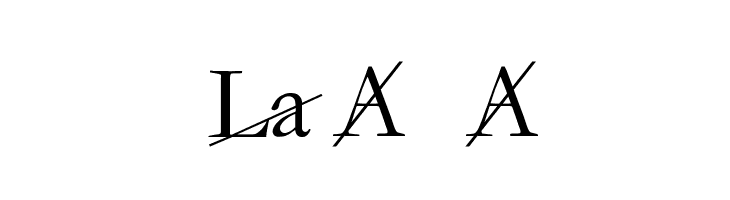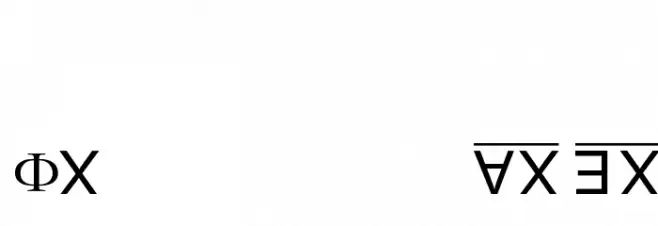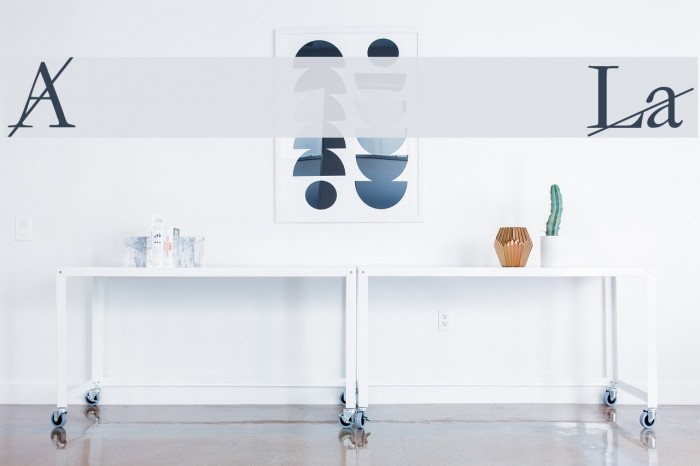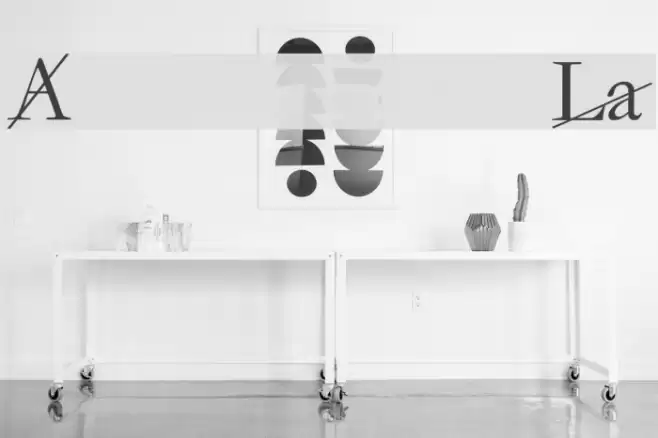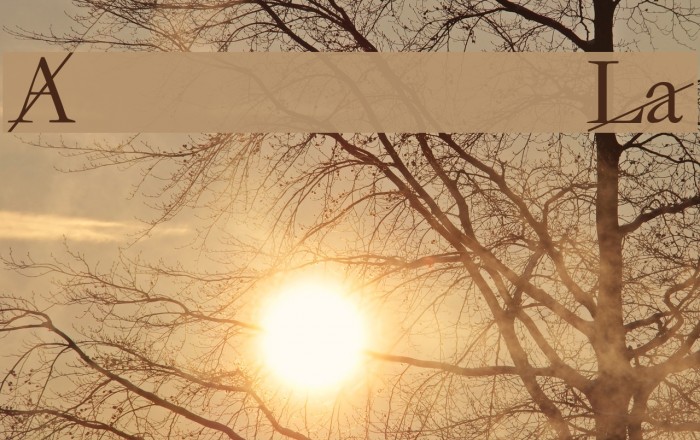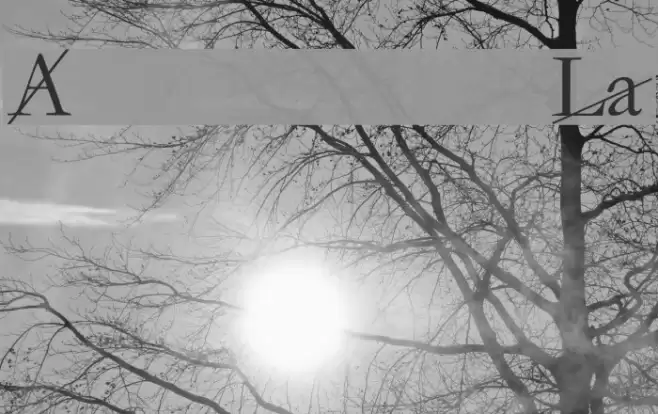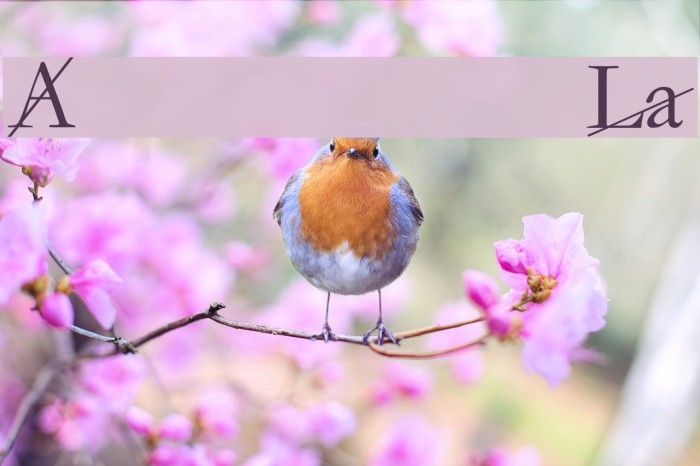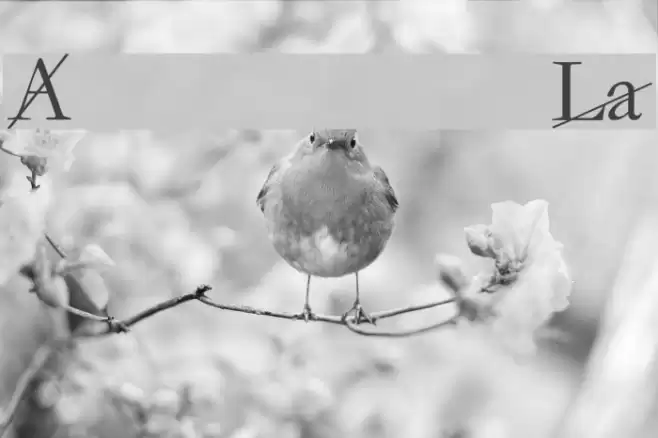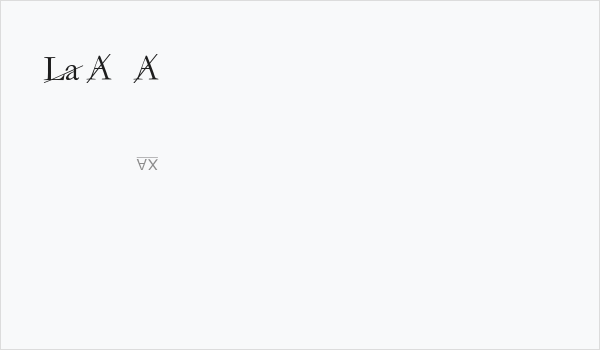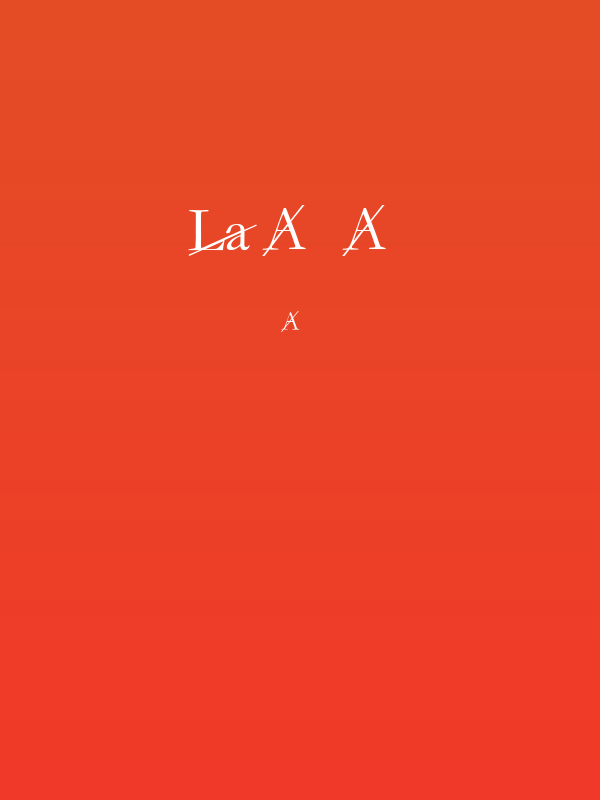
LACAN Font
| Style général | Modern, Intellectual |
| Cas d'utilisation | Logos, Titles, Artistic Displays |
| Projets proposés | Ideal for academic papers, philosophical publications, or modern art projects. |